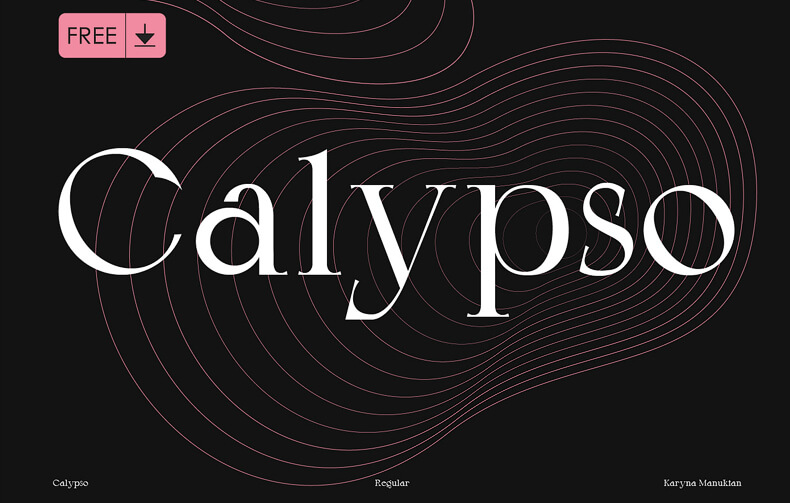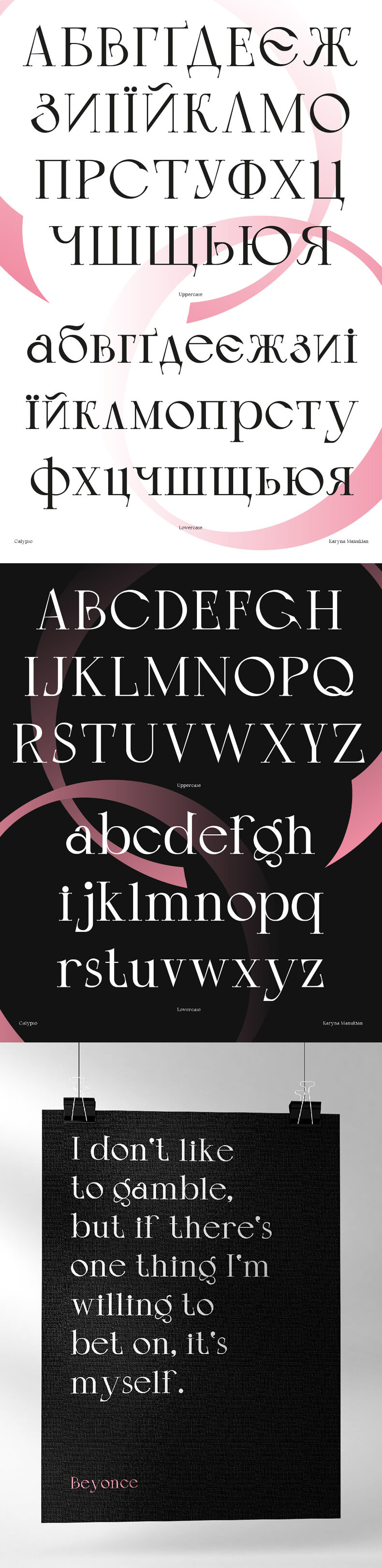
Шрифт - Calypso
Кириллический шрифт с декоративными засечками, который вы можете использовать для красивых дизайнерских заголовков в рекламе, оформлении и других видах дизайна.